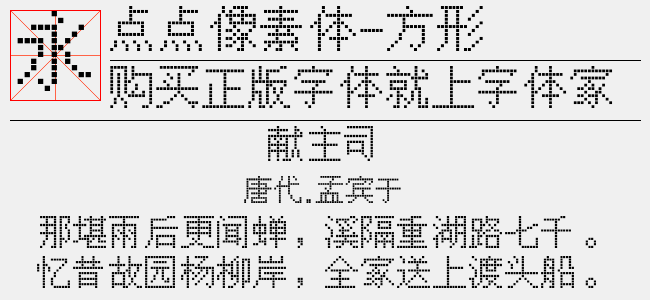
正体(简)中文点阵字Zfull-GB.ttf
正体(简)中文点阵字Zfull-GB.ttf是一款非常漂亮的艺术字体,正体(简)中文点阵字Zfull-GB.ttf字体广泛用于各种书刊、画册的设计印刷中,正体(简)中文点阵字Zfull-GB.ttf字体具有强烈的视觉冲击力,报纸和杂志和书籍
正体(简)中文点阵字Zfull-GB.ttf是一款非常漂亮的艺术字体,正体(简)中文点阵字Zfull-GB.ttf字体广泛用于各种书刊、画册的设计印刷中,正体(简)中文点阵字Zfull-GB.ttf字体具有强烈的视觉冲击力,报纸和杂志和书籍中常用字体, 海报、个性促进品牌标志设计、字体设计、等环境。 正体(简)中文点阵字Zfull-GB.ttf字体是一款用于标题设计方面的字体,由字体下载站提供免费下载,字体下载大全提供最全最新的中、英文字体素材。